디자인 작업을 할 때 폰트 선택은 중요한 부분입니다.
적절한 폰트는 디자인의 분위기를 전달하고 메시지를 효과적으로 표현하는 데 도움이 됩니다.
하지만 다양한 폰트가 존재하기 때문에 어떤 폰트를 선택해야 할지 고민이 될 수 있습니다.
이 글에서는 상업적 사용이 가능한 무료 고딕체 폰트 중에서도 디자인 작업에 활용하기 좋은 5가지 폰트를 추천하고자 합니다.
고딕체란?
고딕체는 한국과 일본에서 산세리프 글꼴을 칭하는 말로 산 세리프(Sans serif)는 세리프(Serif)가 없다('sans')는 뜻입니다.
즉, '세리프(장식용 삐침)가 없는' 글꼴입니다.
획의 굵기가 변하지 않고, 가로획과 세로획이 거의 일정하며 획 끝에 별다른 장식이 없는 것이 특징입니다.
글꼴의 인상이 강하고 직설적인 느낌이므로 제목이나 간판 등에 널리 사용됩니다.
추천 고딕체 무료 폰트
- 수트
구글이 개발한 본고딕(Noto Sans)을 기반으로 제작된 폰트로 한글과 어울리는 영문, 숫자 글꼴이 특징입니다.
9가지 굵기를 제공하며, 가변형 굵기인 Variable 포맷도 지원하고 있습니다.
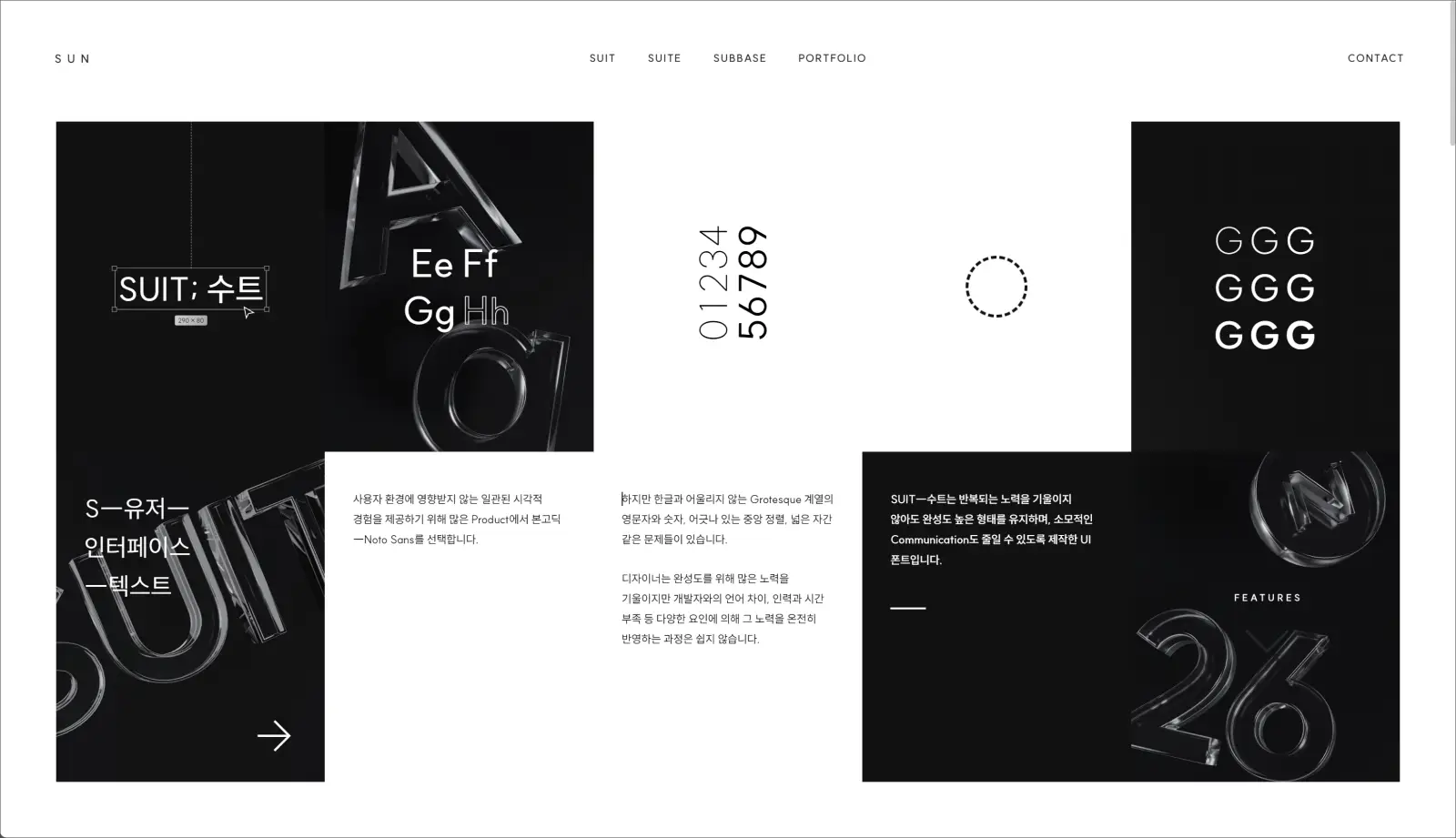
- 프리텐다드
system-ui를 대체하는 글꼴을 목표로 본고딕(Noto Sans), Apple SD 산돌고딕 Neo를 기반으로 제작된 폰트입니다.
자간의 조정, 어울리는 영문 숫자와 기호 등이 첨가되었으며 일본어 폰트도 제공하고 있습니다.
9가지 굵기를 제공하며, 가변형 굵기인 Variable 포맷도 지원하고 있습니다.
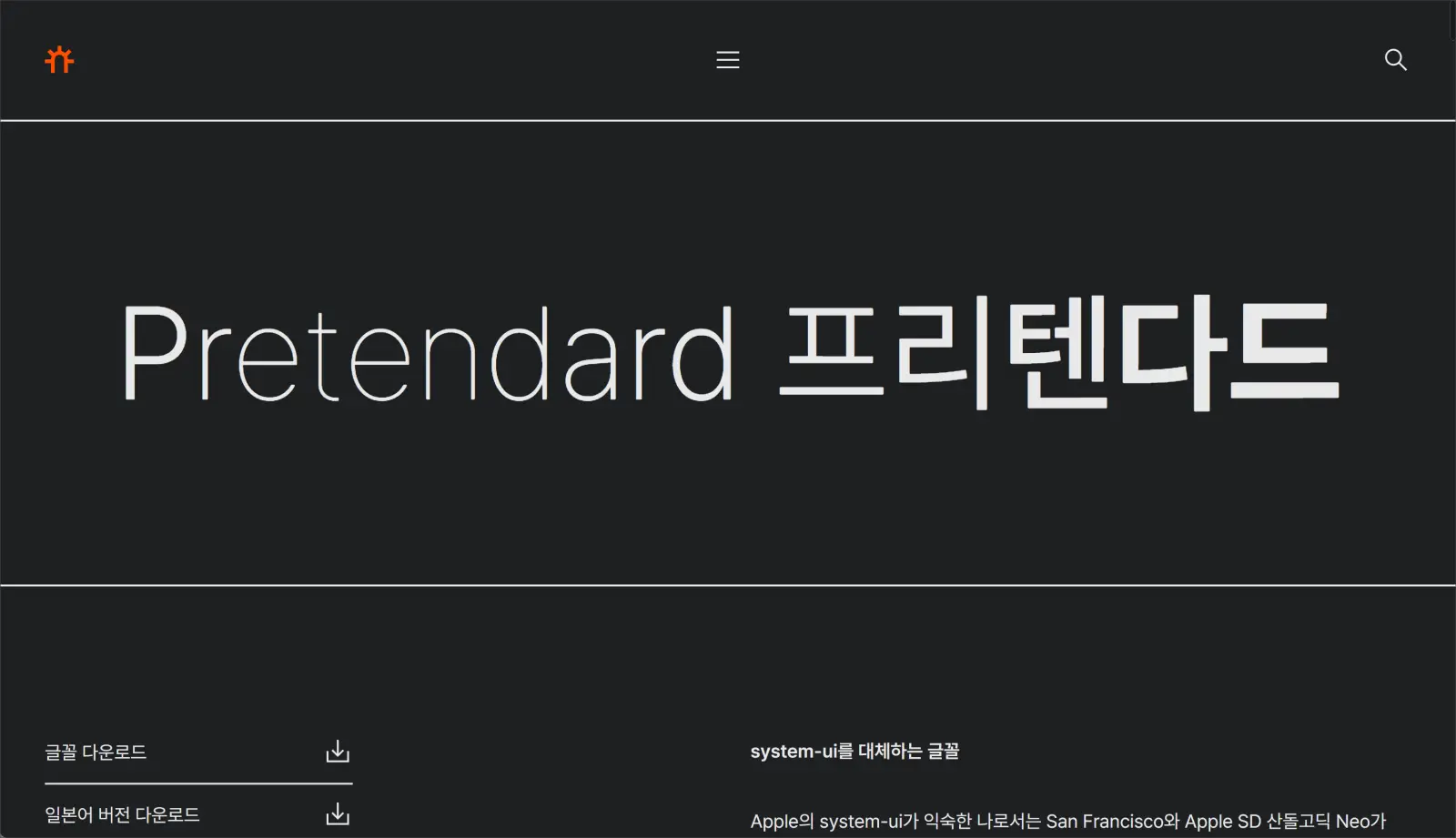
- 에스코어 드림
에스코어 드림은 에스코어디자인에서 개발한 무료 폰트로, 부드럽고 따뜻한 느낌을 주는 디자인으로 서적, 디자인 소재 등에 많이 활용됩니다.
한글과 영문의 호환성이 뛰어나 다양한 디자인 작업에 활용하기 좋습니다.
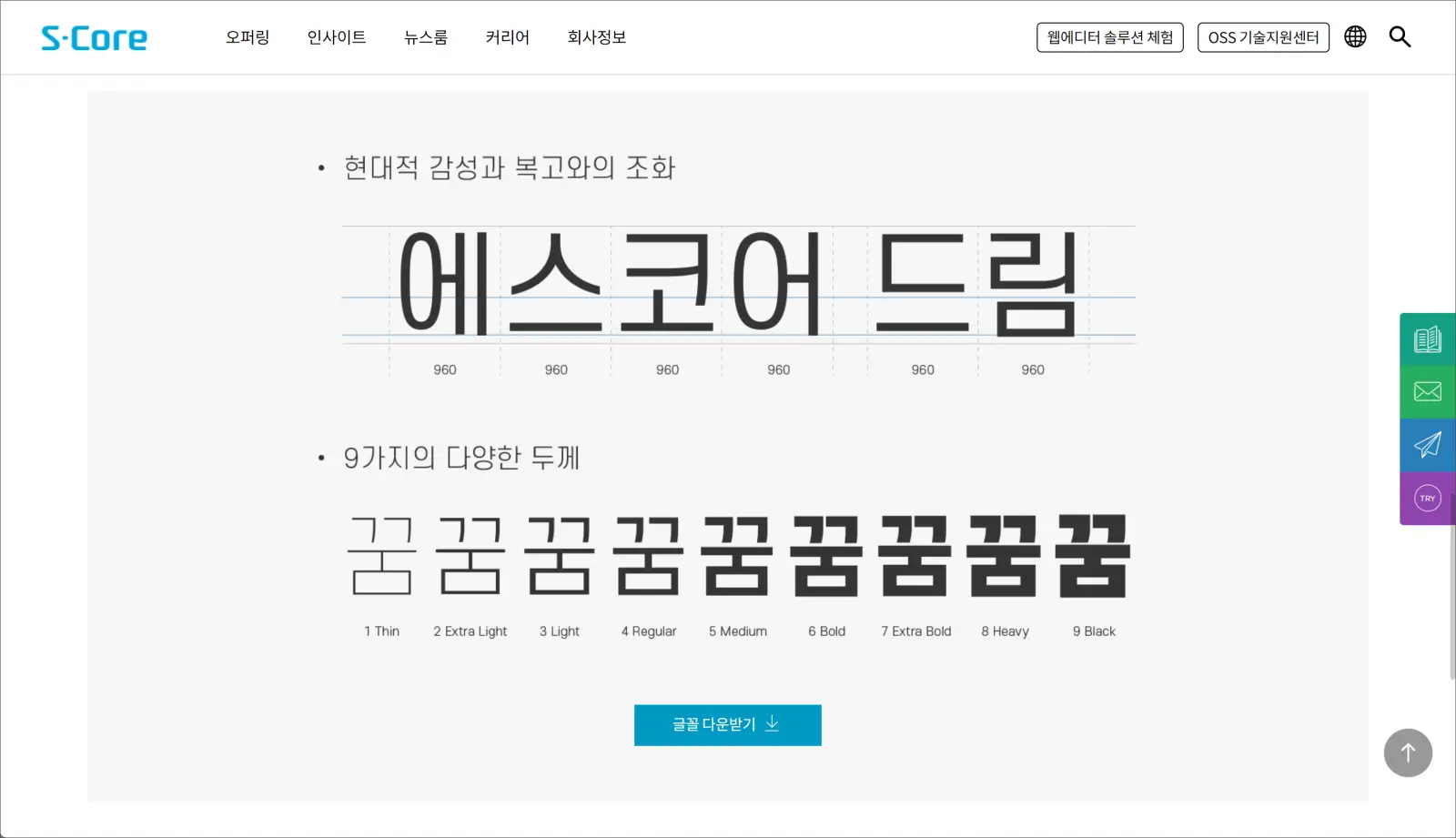
- 나눔스퀘어 네오
네이버에서 만든 브랜드 폰트인 나눔스퀘어 네오는 2022년에 출시되었습니다.
넓은 속 공간과 꽉 찬 모듈로 디자인되어 가독성과 주목성을 높였으며, 다양한 환경에서 문장을 효과적으로 전달하는 데 적합합니다.
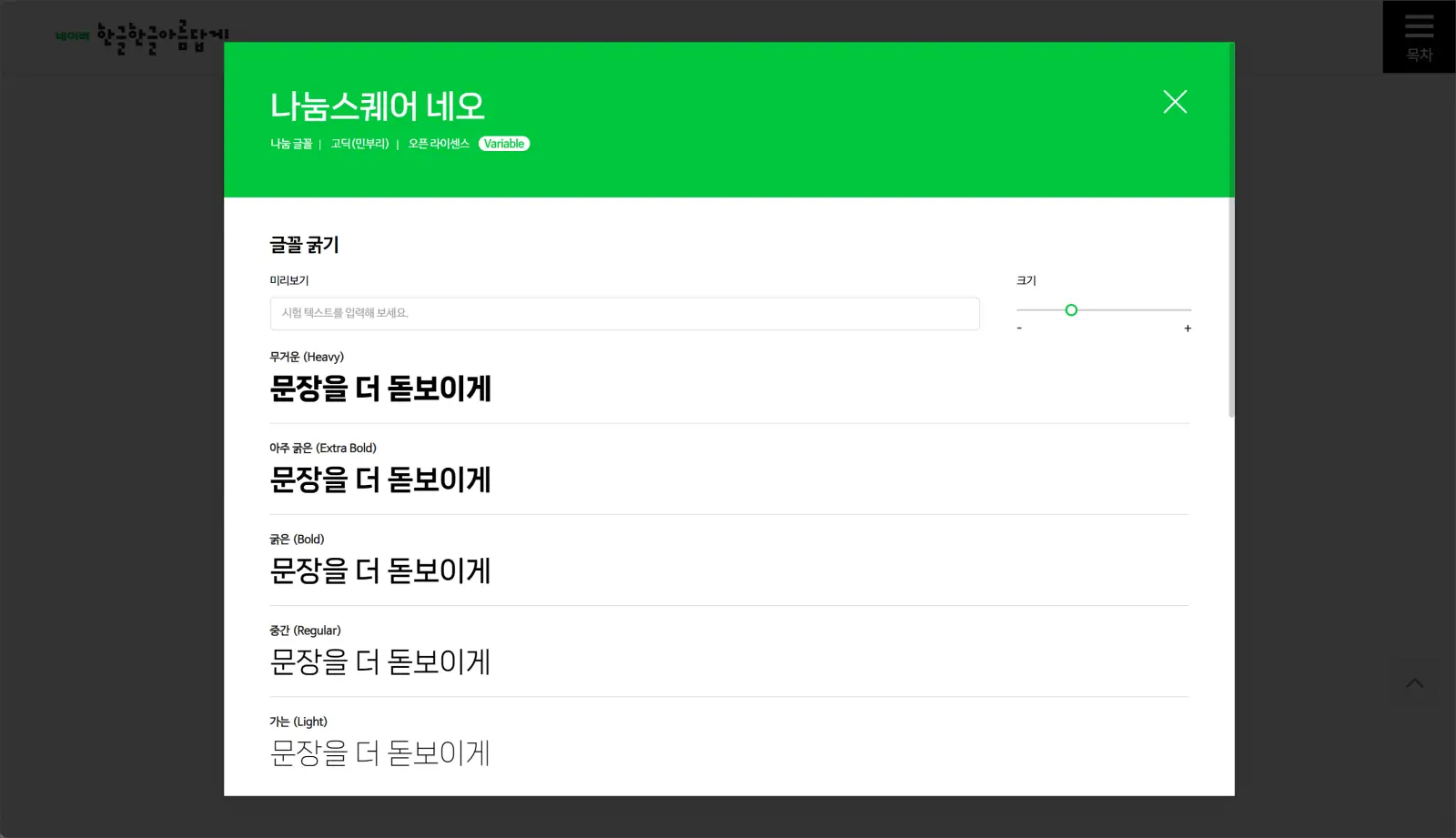
- 페이북 폰트
BC카드에서 제작한 폰트로 둥근 이미지의 속성을 유지하면서 모바일에서도 또렷하게 보일 수 있도록 직선의 요소를 반영한 글꼴입니다. 네 가지 타입이 있습니다.